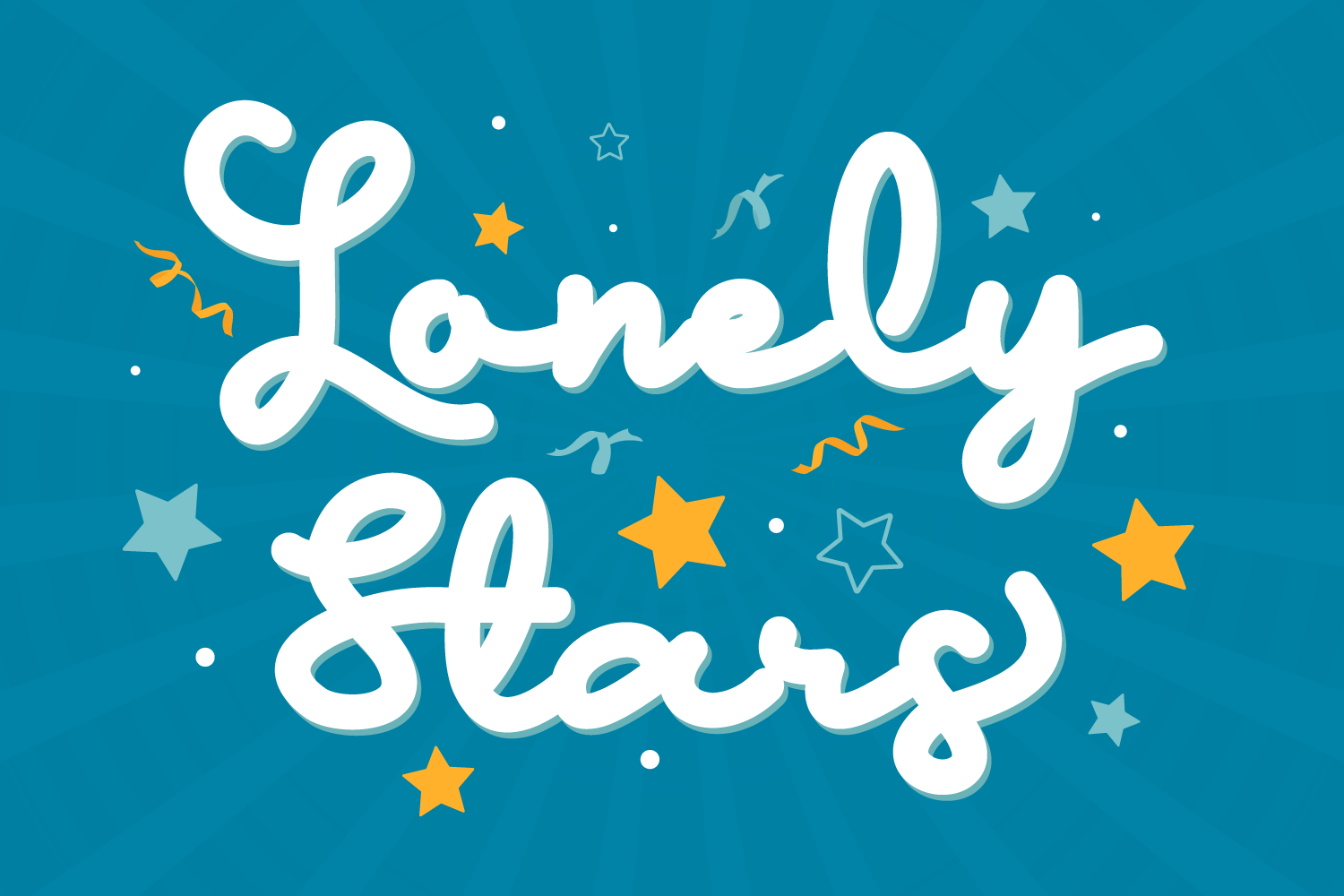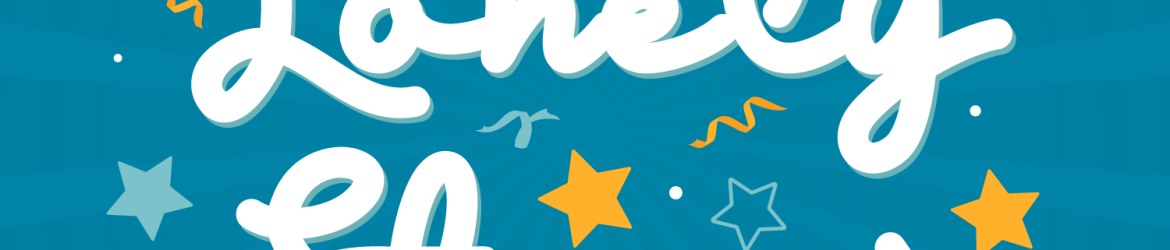
Lonely Star Font – Download Grátis
Esta é uma linda fuente script que flui suavemente. Seu estilo adoravelmente vibrante a torna perfeita para iluminar seus designs. Esta fuente possui PUA encoding, o que significa que você pode acessar todos os caracteres e swashes com facilidade. Perfecto para decorar seu site pessoal ou qualquer design gráfico de forma criativa. Heloyud é um designer talentoso que produziu esta fonte única em estilo manuscrito.